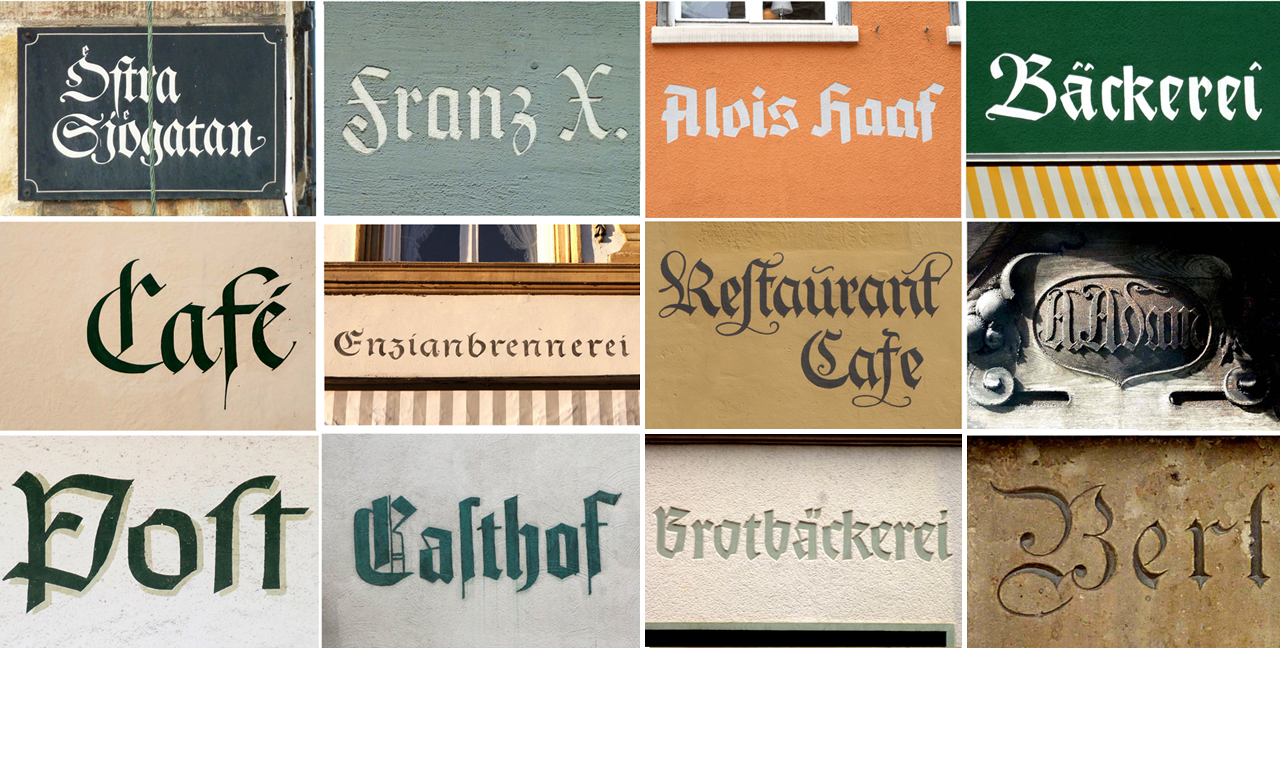
Abbildung:
Gesammelte Fundstücke von unterwegs
Mein Vortragsthema ist in diesem Jahr »Gebrochene Schriften/Gedruckt, gemalt, geschrieben«. Neben schriftgeschlichtlichen Unterscheidungsmerkmalen unseres wunderschönen Kulturgutes zeige ich eine Sammlung aus den unterschiedlichsten Anwendungsgebieten.
In Anlehnung an meinen Vortrag habe ich auch das Workshop-Thema gewählt: »Textur-Experiment/Vom kalligrafischen Grundstich zur kraftvollen Wortmarke«. Schwerpunkt des Workshops ist die Textur. Spielerisch werden die Grundelemente mit Balsaholz aufs Papier gebracht und zu einzelnen Buchstaben und Worten zusammengesetzt. Aus diesen Worten entwickeln wir eine kraftvolle »Wortmarke«, z.B. für ein T-Shirt, ein Sign painting, einen Stempel, eine Postkarte. Das Erlernte ist nicht nur eine Basis für die weitere Auseinandersetzung mit der Kalligrafie, sondern erweitert auch das Schriftrepertoire für Handlettering- Interessierte. Vorkenntnisse sind nicht erforderlich.